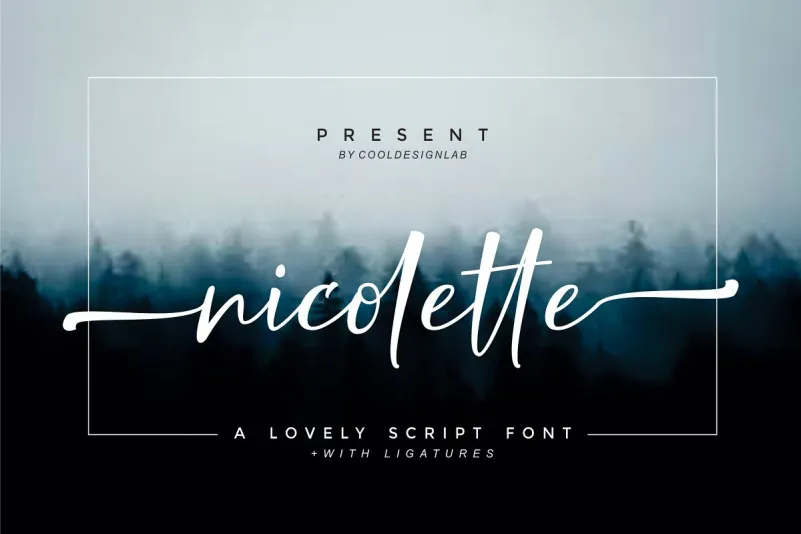
Nicolette Script Font – Download Grátis
A Nicolette Font é uma elegante escolha para quem busca um estilo criativo e sofisticado para seus projetos digitais. Desenvolvida pela 1001fonts, esta é uma fonte script de escrita manual que ganhou um toque moderno, com ondulações aparentes tanto no topo quanto na base dos caracteres. Com seu aspecto moderno e alegre, essa fonte traz elegância ao design sem perder o encanto da letra cursiva. Nicolette é uma opção versátil para diversas necessidades, como rótulos de embalagens, materiais de escritório, cartões de felicitações, assinaturas personalizadas e até mesmo letras musicais ou subtítulos em notícias. Ela se destaca perfeitamente para criações de marca, eventos especiais como casamentos, e também para anúncios promocionais. Esta fonte é perfeita tanto para aqueles que buscam uma adesão natural aos padrões atuais quanto para designers que valorizam um estilo único e chamativo. Não hesite em explorar as inúmeras possibilidades da Nicolette, seja ela utilizada para criar cartazes publicitários, selos de produtos ou até mesmo estampas personalizadas em camisetas. A Nicolette é a escolha perfeita para aqueles que desejam incorporar elegância e criatividade na sua identidade visual e no seu design gráfico.